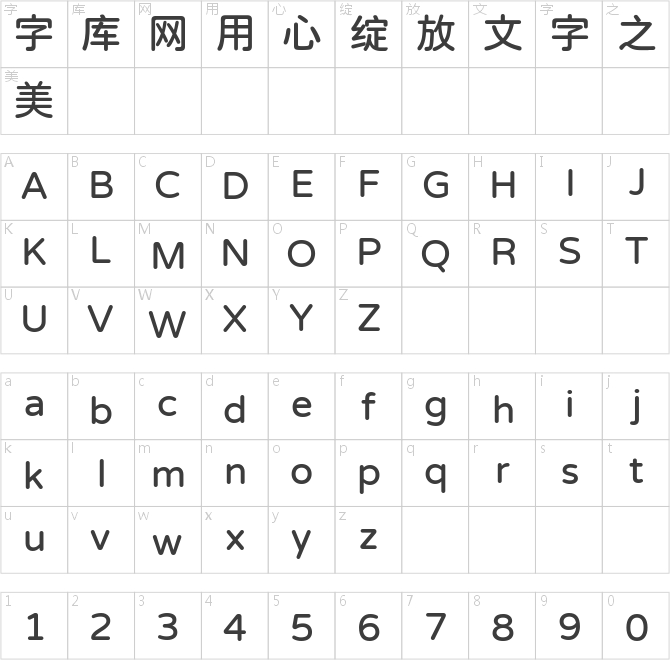
字体名称: 极影毁片荧圆
极影毁片荧圆
极影毁片荧圆介绍
极影毁片荧圆是一款使用小杉圆体为底本,使用未来圆进行增补的自由字体。
jfopen粉圆是繁体中文基准的字体,而繁体中文的字体都存在字形标准 不一而造成的字形混乱问题。
比如草字头、走之旁、绞丝旁、令字的写法、羽宇的写法、户字的写法等等。
甚至同一字体里面,同一偏旁字形都会存在 两种不同的写法。这造成了极影毁片圆后续维护的庞大压力。
极影毁片圆采 用了鄙人手动修正字形来解决上述问题,但不可避免会使得字的重心更加混乱。
所以我产生了放弃粉圆,直接使用小杉圆体作为底本,同时直接使用简 体中文字形的思源系图体来增补,
以达到大幅减少后续维护目的的重制极影 毁片圆的想法。 未来荧黑是将思源黑体进行拔脚,并重新调整字的重心的字体。
由未来 荧黑修改而成的未来圆,在字形上最为接近小杉圆体本来的样子。所以我采 用了未来圆作为增补使用的字体来源。
具体的操作如下。首先我将小杉圆体的字分为两组,一组是GB2312已经收录的字,另一组是其他的字。
后者直接收录,前者手动挑选字形和规范字写法相同或十分相近的字保留收录,其余日本汉字字形的汉字放弃。
剩余的汉字将未来圆稍稍横向拉伸后增补。